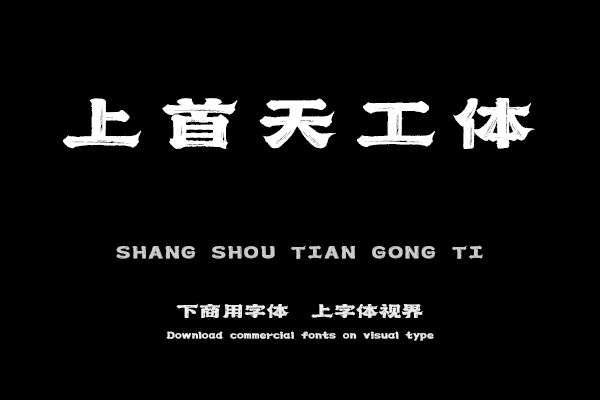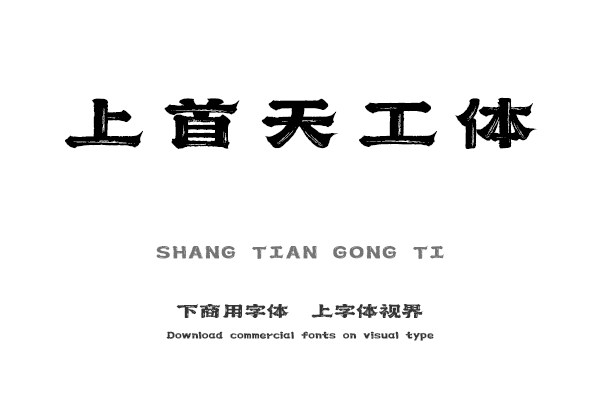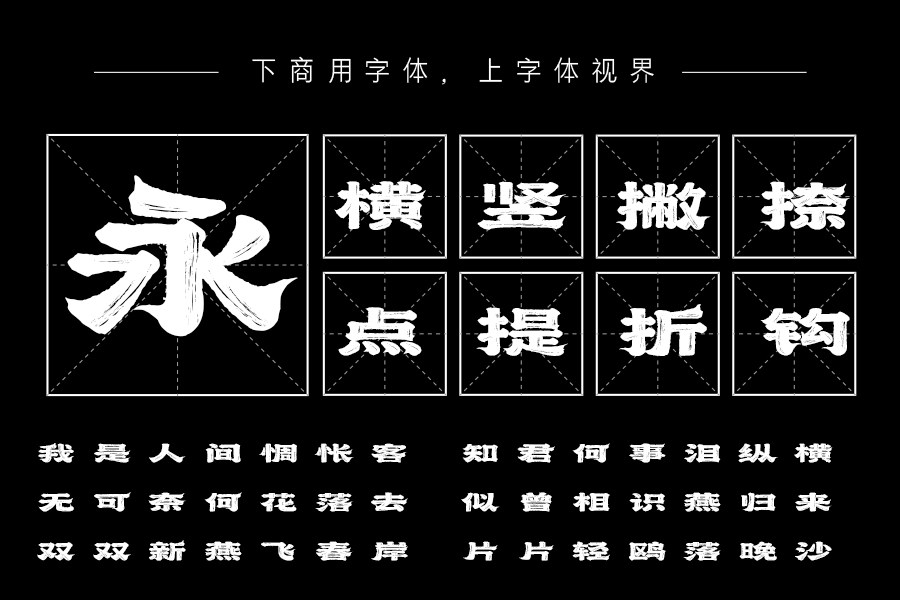
上首天工体,笔触整体较为粗重,横画、竖画和点画都富有曲线美。整款字体看起来端正复古而又神采⻜扬!字体字形的起笔、收笔处都有尖锐的装饰角,笔画之中留出的白痕使字体......购买须知:“下载服务费”与“字体VIP”所获得字体 仅用于个人非商用, 商用请联系付费授权。本字体为电脑用字,手机没有root权限不支持直接手机换字(手机如何root,请自行百度搜索教程)。购买前请先 了解清楚后再付款 ,字体为虚拟产品无法回收 一旦购买不支持退款。